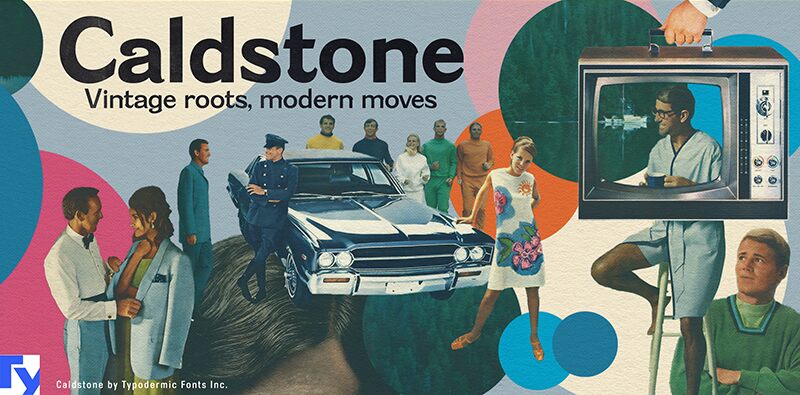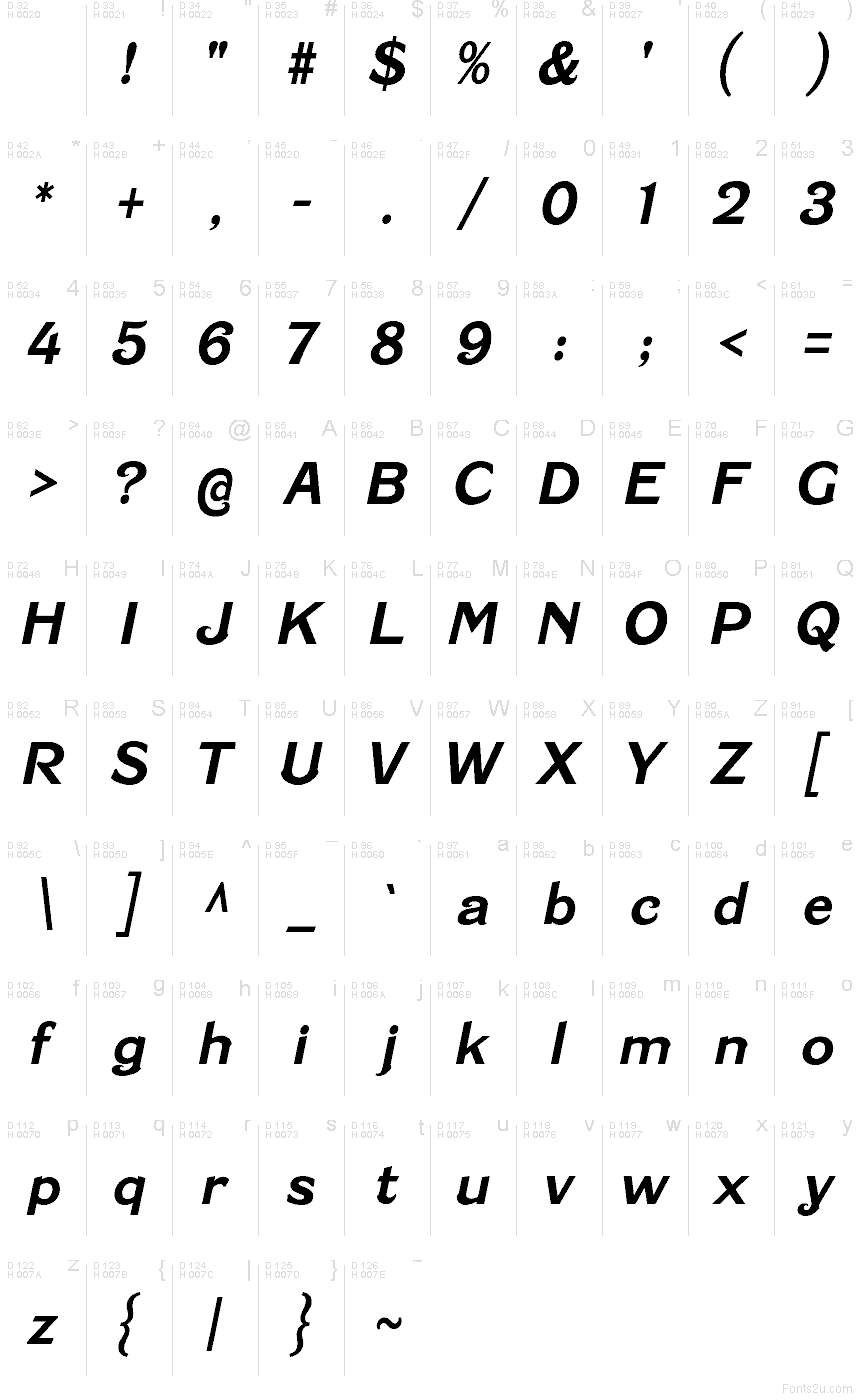
Caldstone è un carattere sans serif display ispirato alle scritte espressive degli anni '10 e ai revival ornamentali degli anni '60. I riccioli decorativi e le grazie — dettagli più comuni nel design dei caratteri serif — gli conferiscono una personalità distintiva, mentre le proporzioni pulite e la spaziatura curata lo rendono perfettamente a suo agio nei layout moderni.
Invece di limitarsi a rievocare una singola fonte antica, Caldstone fonde il fascino dell'inizio del XX secolo con una versatilità contemporanea. Il suo carattere caldo ed esuberante offre un'alternativa ai font sans serif minimalisti, rendendolo adatto a branding, design editoriale, packaging e ogni altro tipo di tipografia orientata all'impatto visivo.